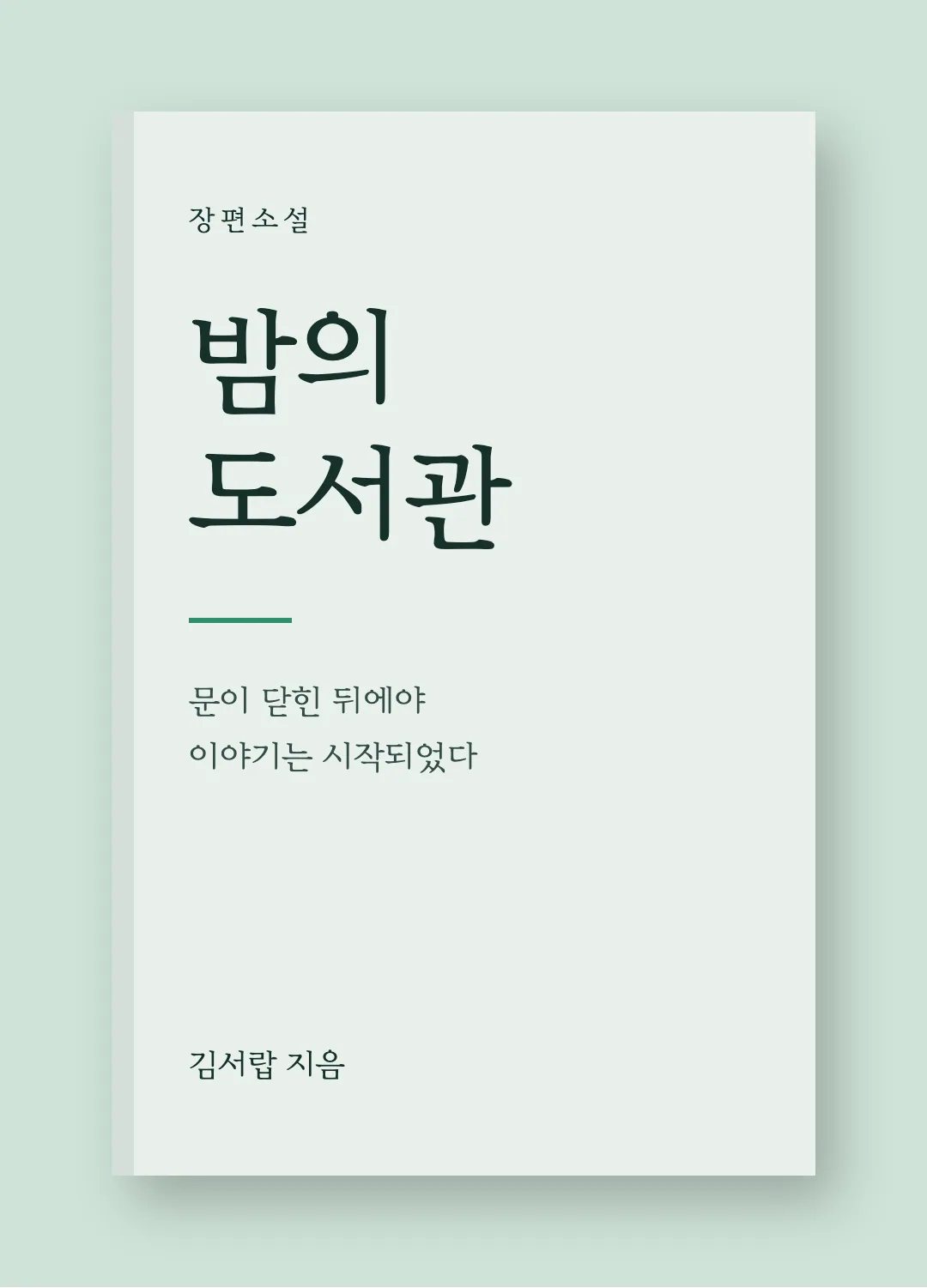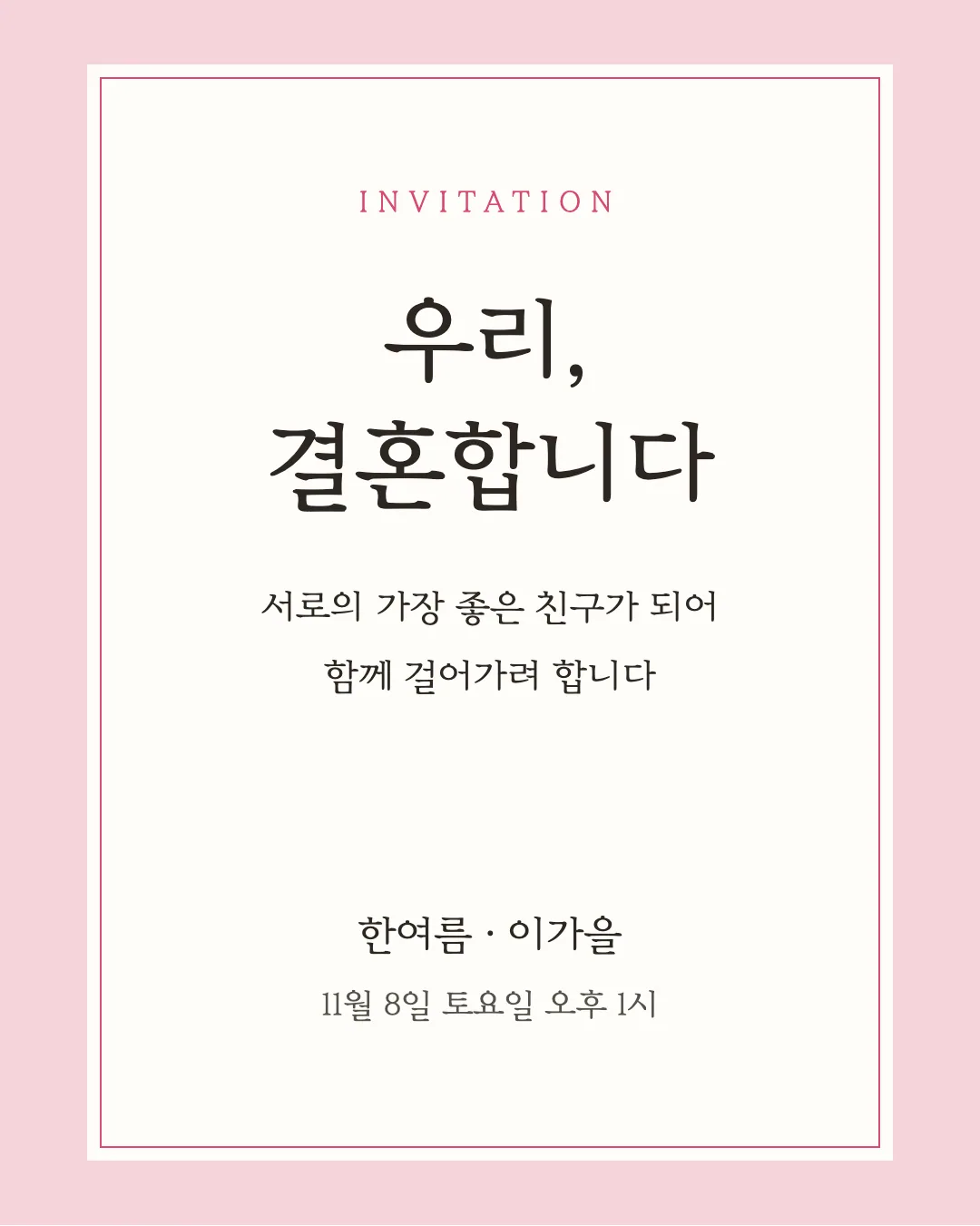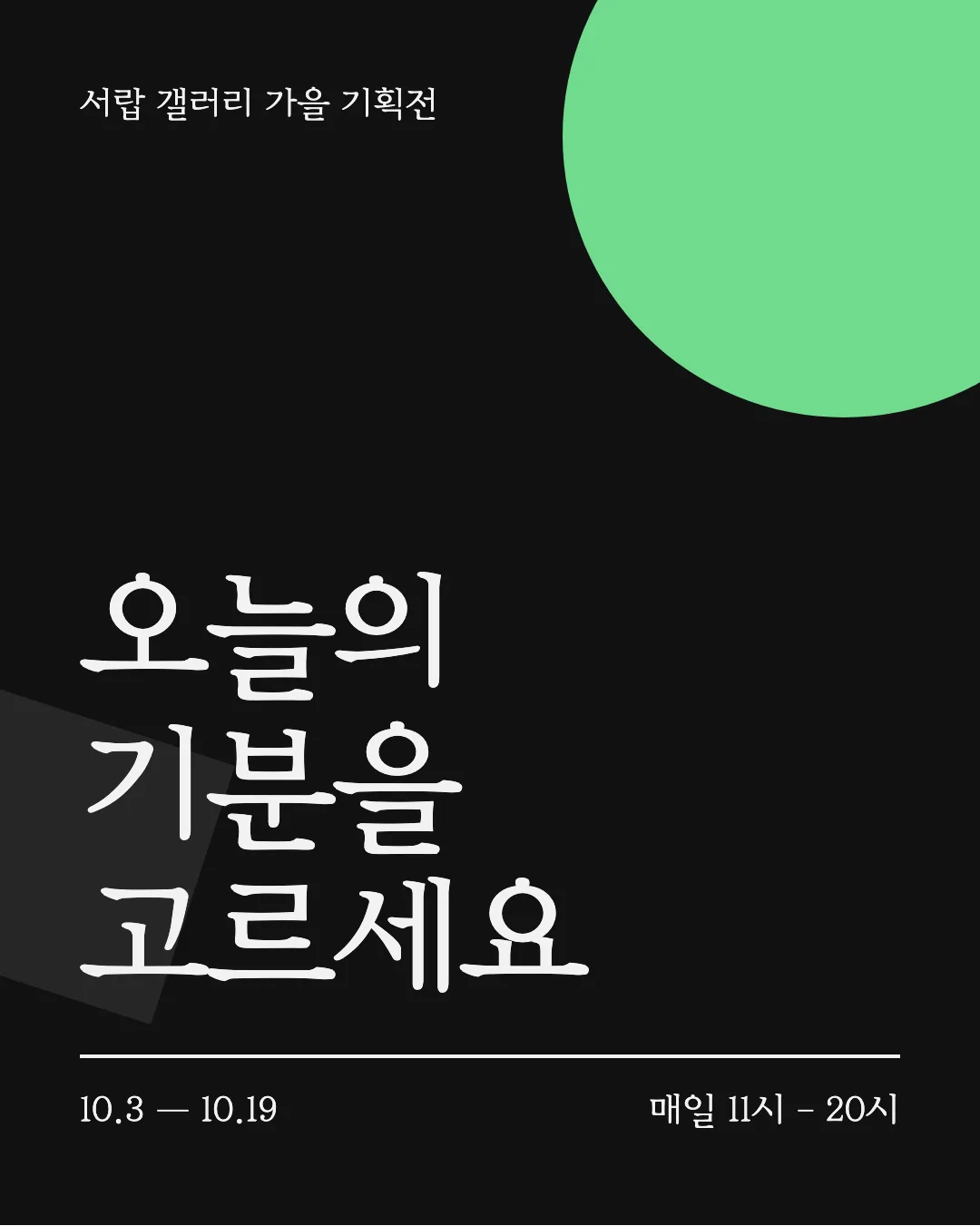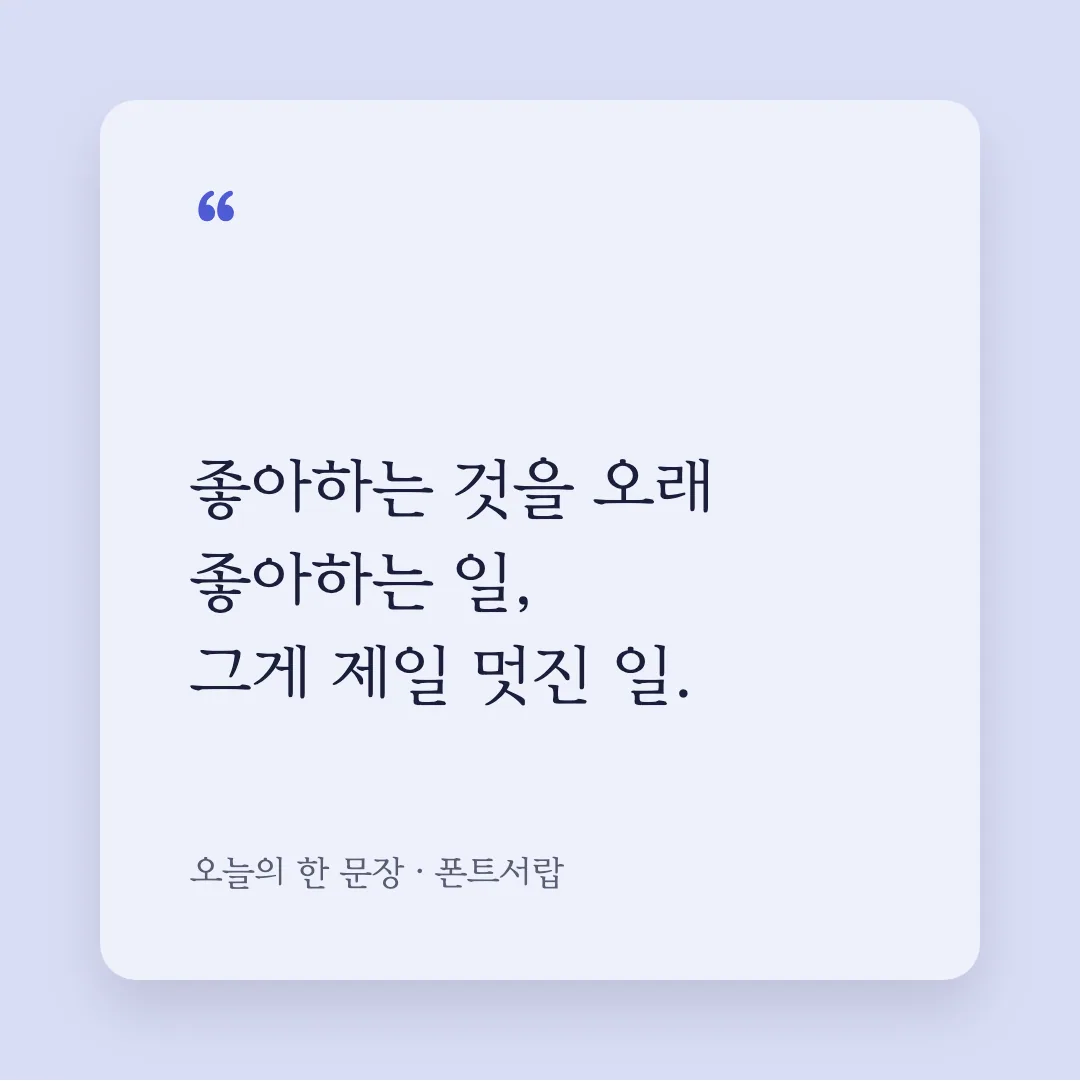
학교안심 산뜻바탕
Hakgyoansim Santteutbatang
- 제작
- 한국교육학술정보원 (KERIS)
- 형태
- 명조·바탕
- 스타일
- 2가지
한국교육학술정보원(KERIS)이 학교에서 저작권 걱정 없이 쓰도록 배포하는 학교안심 폰트 중 본문용 명조입니다. 교재, 가정통신문, 긴 글에 어울립니다.